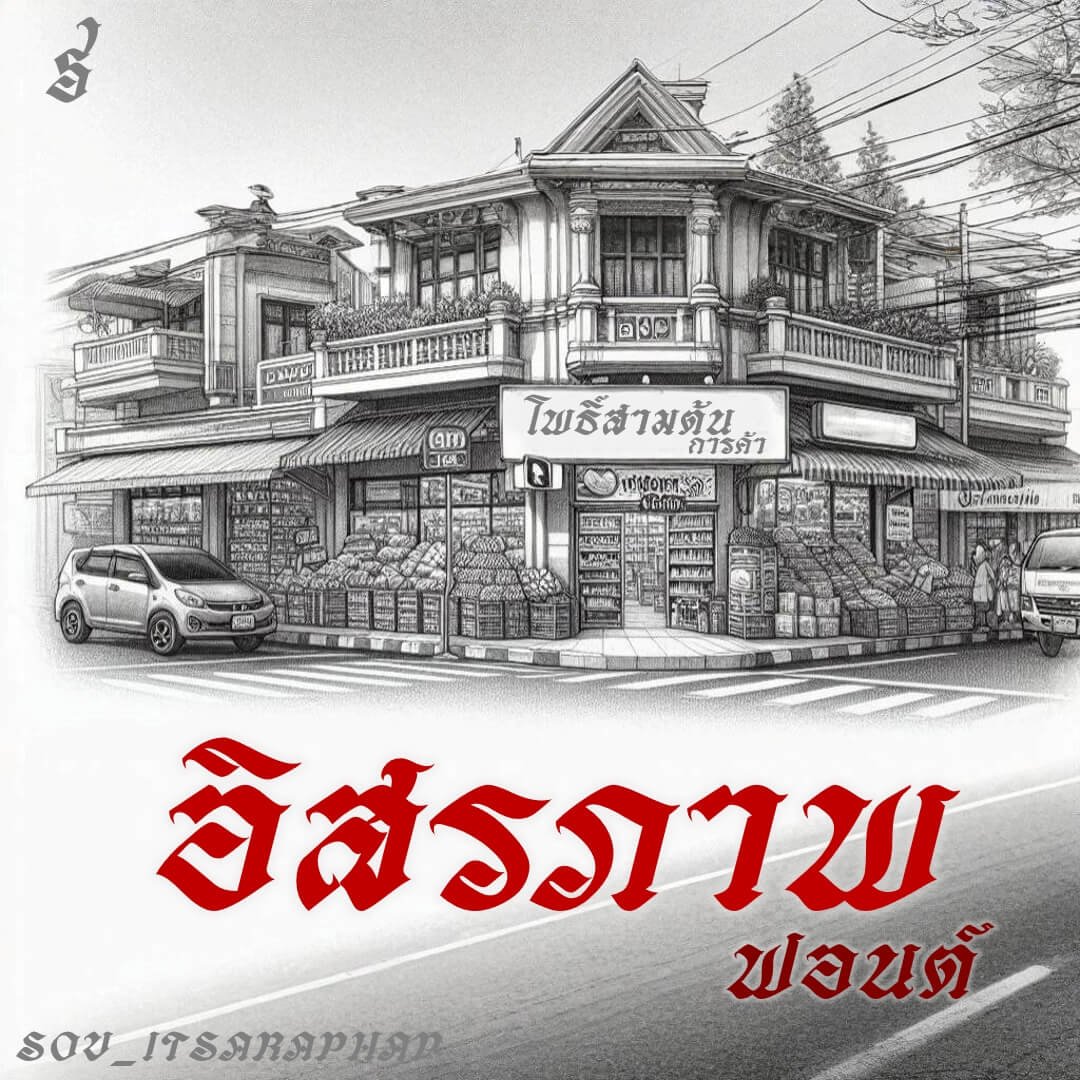
อิสรภาพ (SOV_itsaraphap)
ฟอนต์อิสรภาพ รูปแบบจากป้ายร้านค้าที่เห็นมาแต่เด็กเมื่อราว 40-50 ปีก่อน นั่งรถเมล์ผ่านถนนอิสรภาพ ไปบ้านอาม่าแถวลาดหญ้า ท่าดินแดง หลายร้านยังคงเปิดกิจการอยู่
หมายเหตุ เสน่ห์ของป้ายร้าน คือความคล้ายแต่ไม่เหมือน ขอบคุณ เพจไทยโป ที่รวบรวมรูปไว้จากหลายหลายพื้นที่ ฟอนต์นี้ไม่ได้ยึดต้นแบบจากป้ายร้านใดร้านหนึ่ง แต่เน้นที่เส้นบนยึกๆ และคุมสระบนไม่สูงเกิน… กินที่น้อย